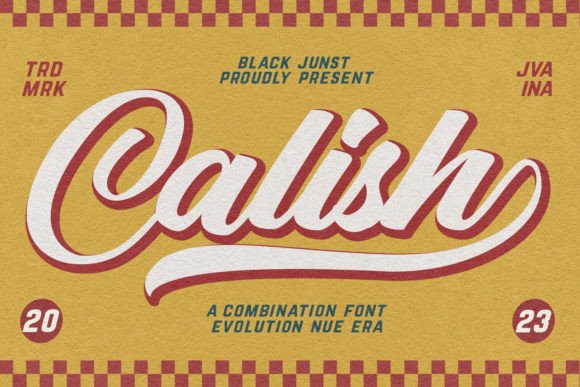
Calish
Calish – A Fonte Retro que Une Originalidade e Modernidade
Se você busca uma tipografia que traga carisma retro sem perder o toque contemporâneo, a Calish é a escolha perfeita. Desenvolvida com curvas delicadas e traços marcantes, ela transforma qualquer projeto em uma obra‑de‑arte visual, tornando‑a ideal para branding, embalagens, convites e peças digitais.
Principais Características da Calish
- Estilo Retro Autêntico: inspira-se nas tipografias dos anos 60‑70, porém com ajustes modernos que evitam o visual ultrapassado.
- Curvas Sedutoras: o design exclusivo das curvas confere à fonte um aspecto sedutor e ao mesmo tempo legível, perfeito para chamar a atenção do público.
- Versatilidade de Uso: funciona impecavelmente em títulos, logotipos, banners, pôsteres e até em interfaces de aplicativos.
- Facilidade de Leitura: apesar do estilo ornamentado, a Calish mantém ótima legibilidade em tamanhos pequenos.
Por Que a Calish Vai Elevar Seus Projetos?
Ao escolher a Calish, você garante:
- Um design mais atraente que destaca sua marca da concorrência.
- Uma identidade visual única, graças ao traço original que poucos designers utilizam.
- Flexibilidade para aplicar em múltiplas plataformas – impressão, web e mobile.
- Um toque de nostalgia moderna que ressoa com diferentes faixas etárias.
Calish não é apenas mais uma script font; ela representa a união perfeita entre origem retro e inovação atual. Se o seu objetivo é criar designs que cativem e permaneçam na memória do público, esta fonte é a sua aliada definitiva. Experimente Calish hoje mesmo e descubra como ela pode transformar a percepção visual da sua marca.